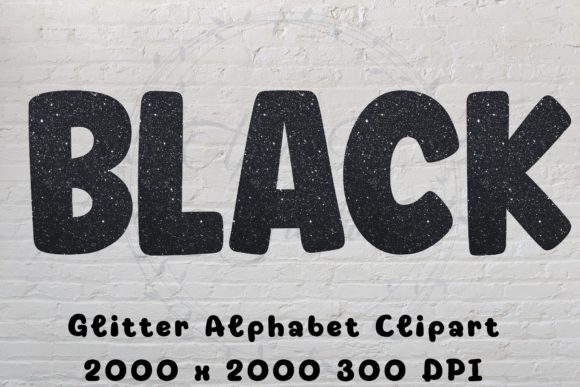
Black Glitter Alphabet Clipart
์˜ฌ๋ฐ”๋ฅธ ๋””์ž์ธ ์š”์†Œ๋ฅผ ์ฐพ๋Š” ๊ฒƒ์€ ์–ด๋ ค์šธ ์ˆ˜ ์žˆ์ง€๋งŒ Black Glitter Alphabet Clipart๋Š” ์ž‘์—…์„ ์ฆ‰์‹œ ํ–ฅ์ƒ์‹œํ‚ค๋Š” ๋›ฐ์–ด๋‚œ ์ปฌ๋ ‰์…˜์„ ์ œ๊ณตํ•ฉ๋‹ˆ๋‹ค.
์ •๋ฐ€ํ•˜๊ฒŒ ์ œ์ž‘๋œ Black Glitter Alphabet Clipart๋Š” ๊น”๋”ํ•œ ๋ฒกํ„ฐ, ๋ถ€๋“œ๋Ÿฌ์šด ํƒ€์ดํฌ๊ทธ๋ž˜ํ”ผ ๋ฐ ์•ˆ์‹ฌํ•  ์ˆ˜ ์žˆ๋Š” ์ƒ์—…์šฉ ๋ผ์ด์„ ์Šค๋ฅผ ์ œ๊ณตํ•ฉ๋‹ˆ๋‹ค.
POD(์ฃผ๋ฌธํ˜• ์ธ์‡„) ์ œํ’ˆ, ๊ฒฐํ˜ผ์‹ ์ดˆ๋Œ€์žฅ ๋˜๋Š” ์†Œ์…œ ๋ฏธ๋””์–ด ๊ทธ๋ž˜ํ”ฝ์„ ๋งŒ๋“ค ๋•Œ Black Glitter Alphabet Clipart๋Š” ์ด์ƒ์ ์ธ ์„ ํƒ์ž…๋‹ˆ๋‹ค.